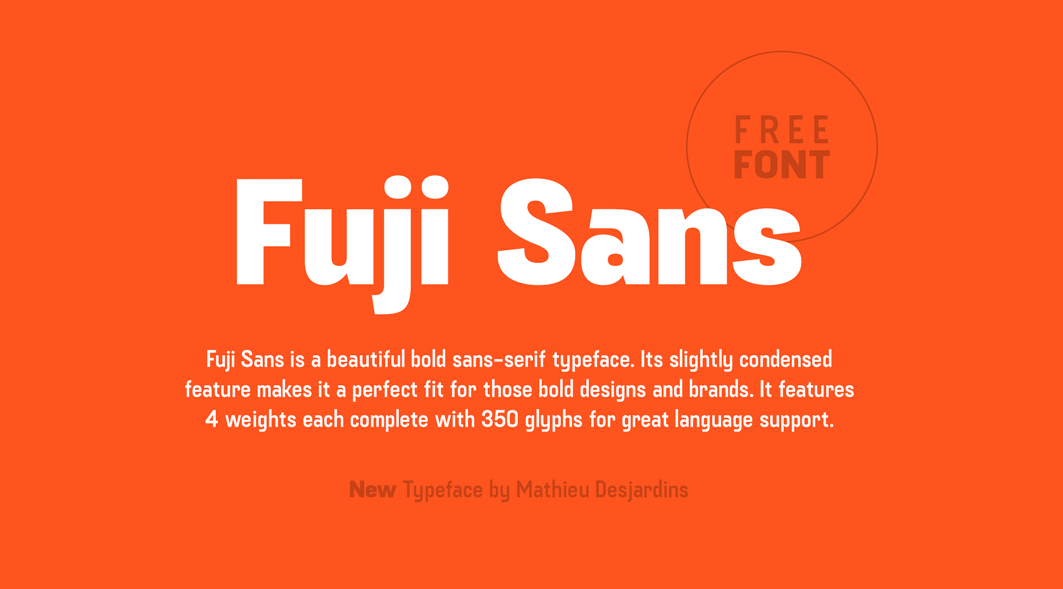
A Fuji Sans é uma elegante fonte de tipo aberto desenvolvida por Mathieu Desjardins. Introduzida para se encaixar perfeitamente no universo profissional, esta fonte não apenas oferece uma aparência moderna e clara, mas também um conjunto adequado de itálico e negrito para garantir que seja fácil de ler em todas as aplicações. Com seu designer australiano, Hamilton, a Fuji Sans é ideal tanto para design editorial quanto para gráficos digitais. Seu aspecto clean e minimalista torna-a uma escolha confiável para estilos modernos ou descolados sem perder um toque de sofisticação. Seja em websites, relatórios, materiais publicitários ou designs digitais, a Fuji Sans é uma opção consistente e profissional que se assegura de transmitir sua mensagem de maneira clara e elegante.